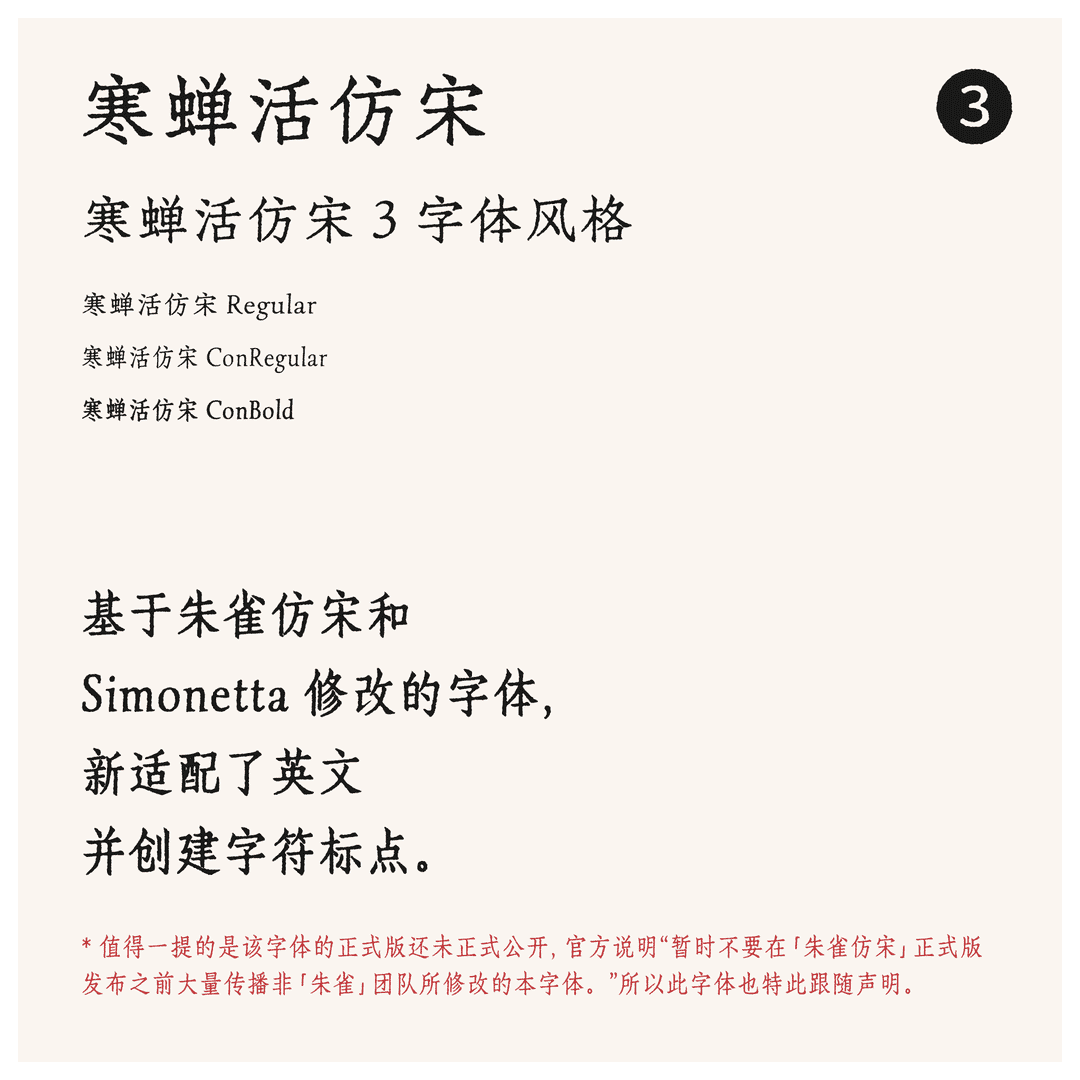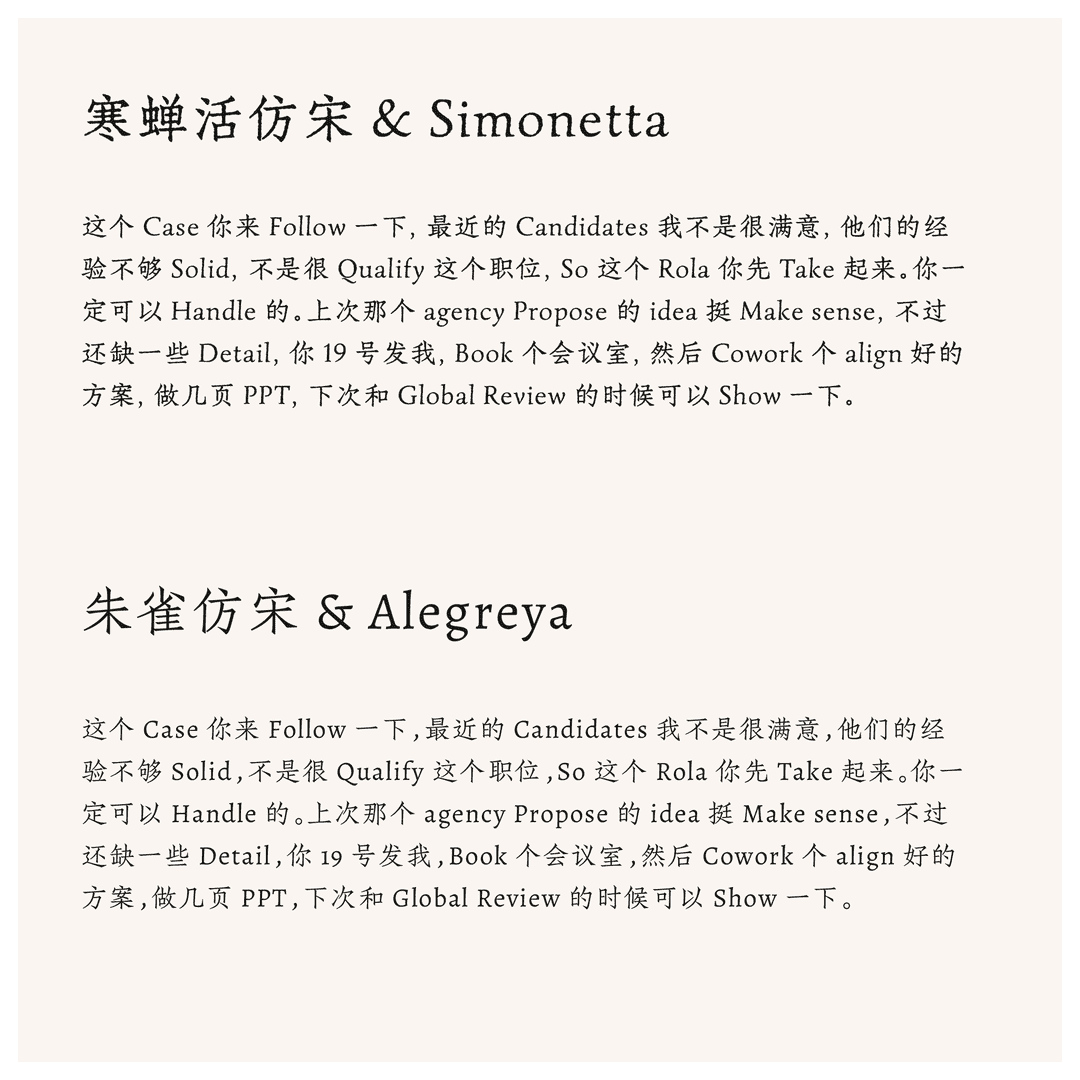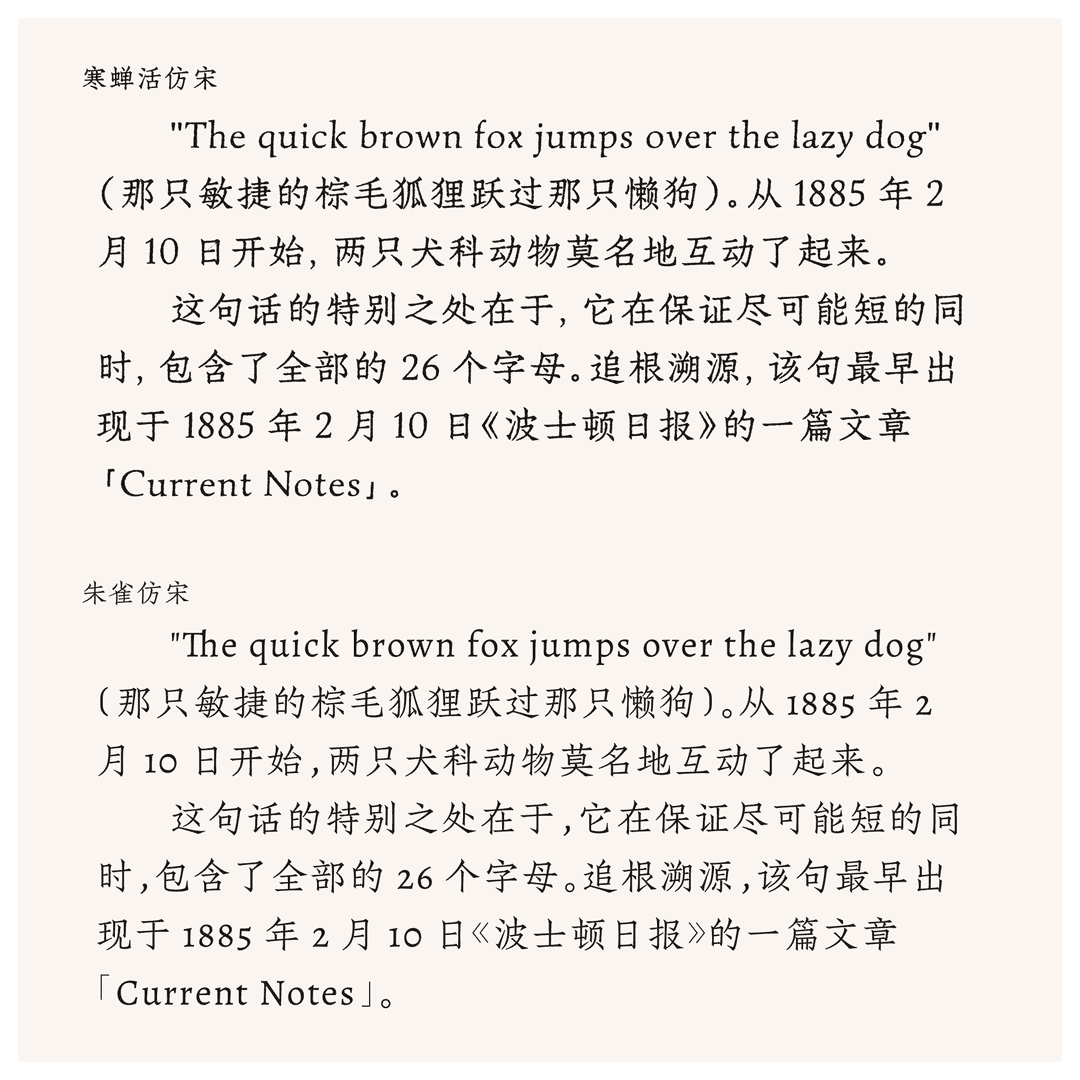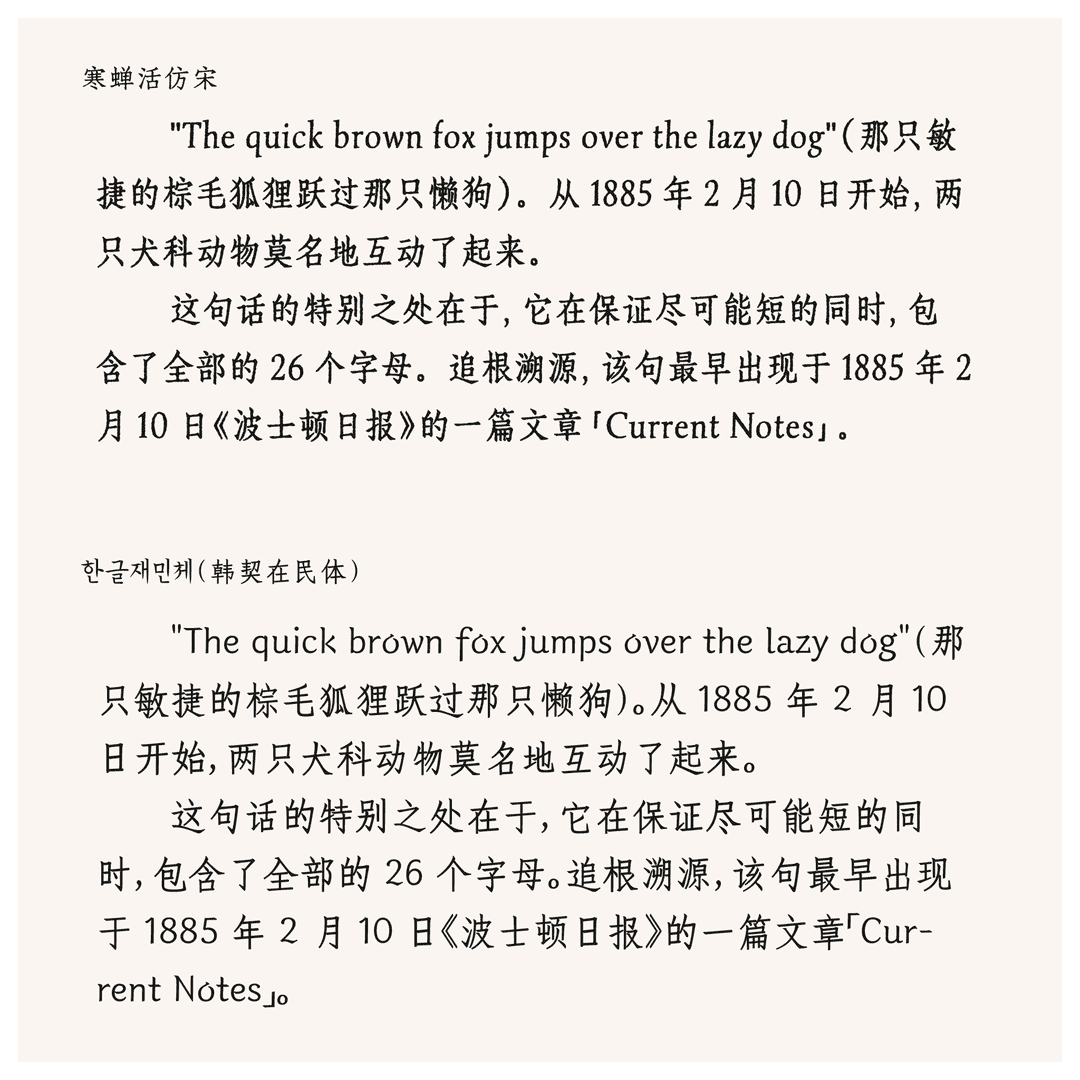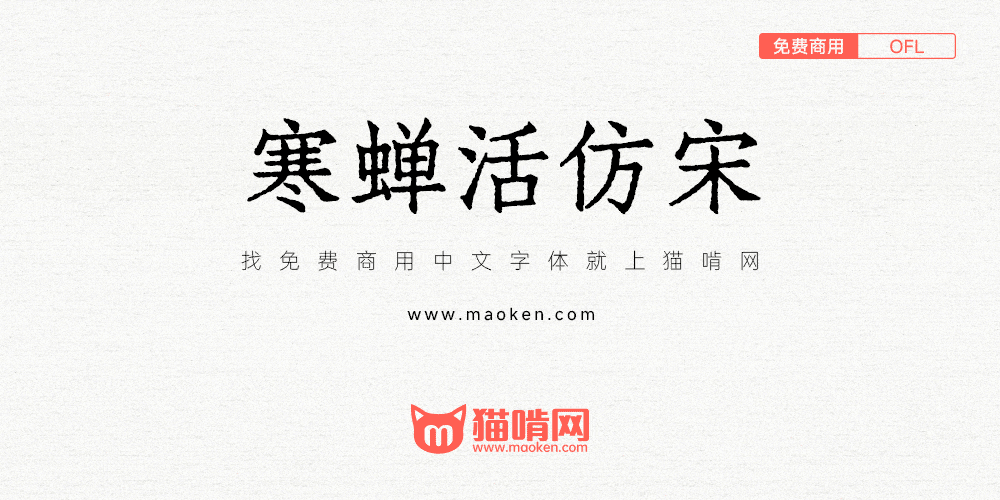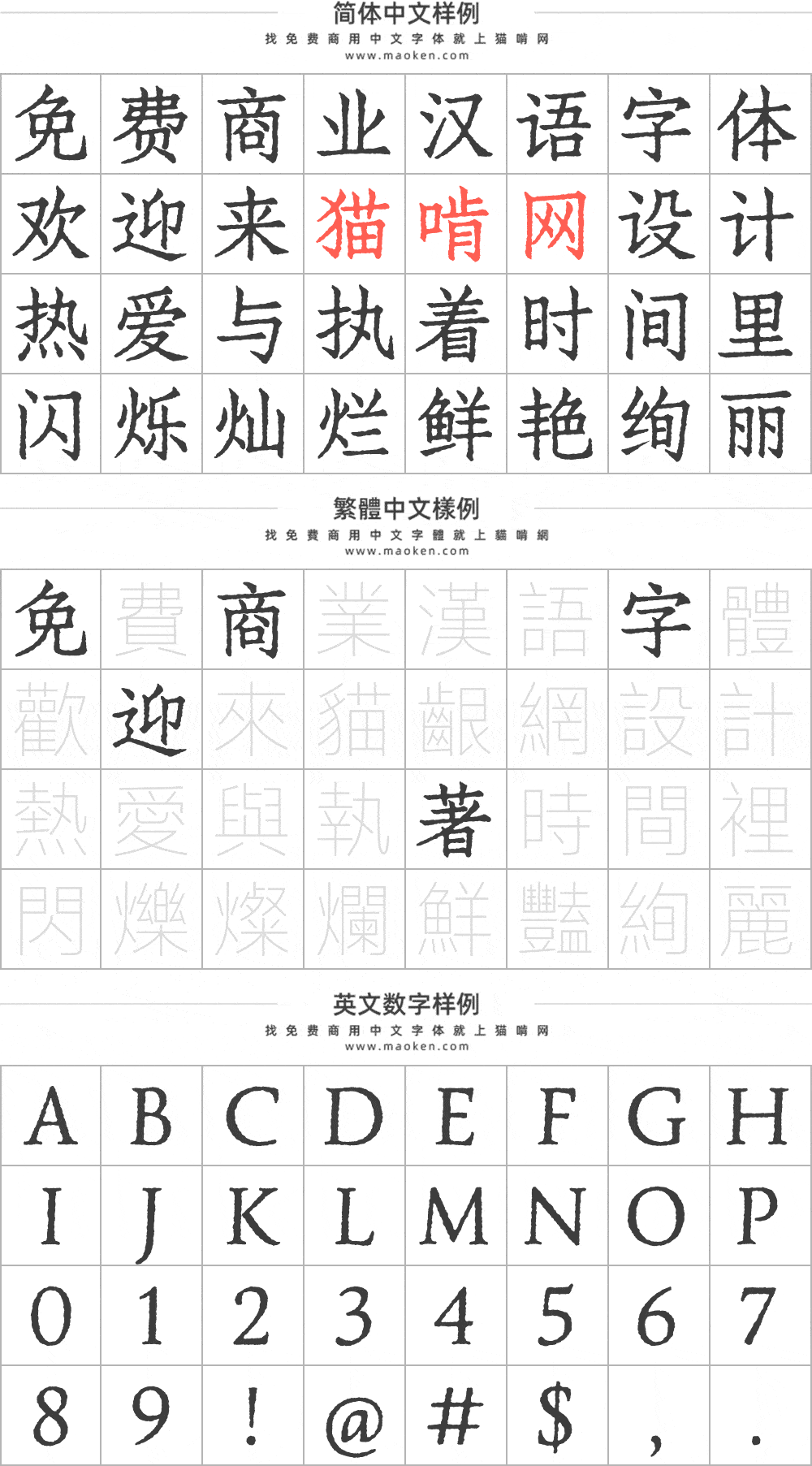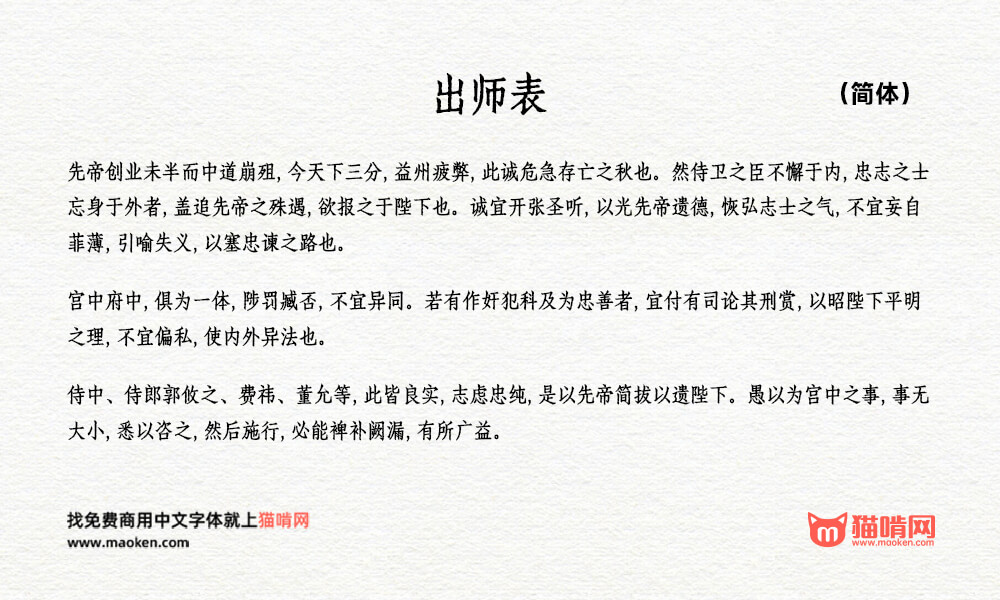
寒蝉活仿宋:基于朱雀仿宋和Simonetta修改的字体
寒蝉活仿宋是基于朱雀仿宋和Simonetta修改的字体,新适配了英文,并创建字符标点。
ConRegular 和 ConBold 两种风格,“病”字存在问题
如楼下所言,【制度】的“制”存在硬伤,只显示“刂”
制度的制,不能正常显示,只显示刂
寒蝉活仿宋v0.100:1.字母 J 左下角的勾不明显,建议优化. 2.字母ABEF较窄,CDGH较宽,视觉效果欠佳,建议优化或者更换配套的英文字体
(与本字体无关)对照例图有个问题:朱雀仿宋配的是我专门修改的Alegreya,其字重、Qg、数字等与例图中皆不同,不好作为对照。